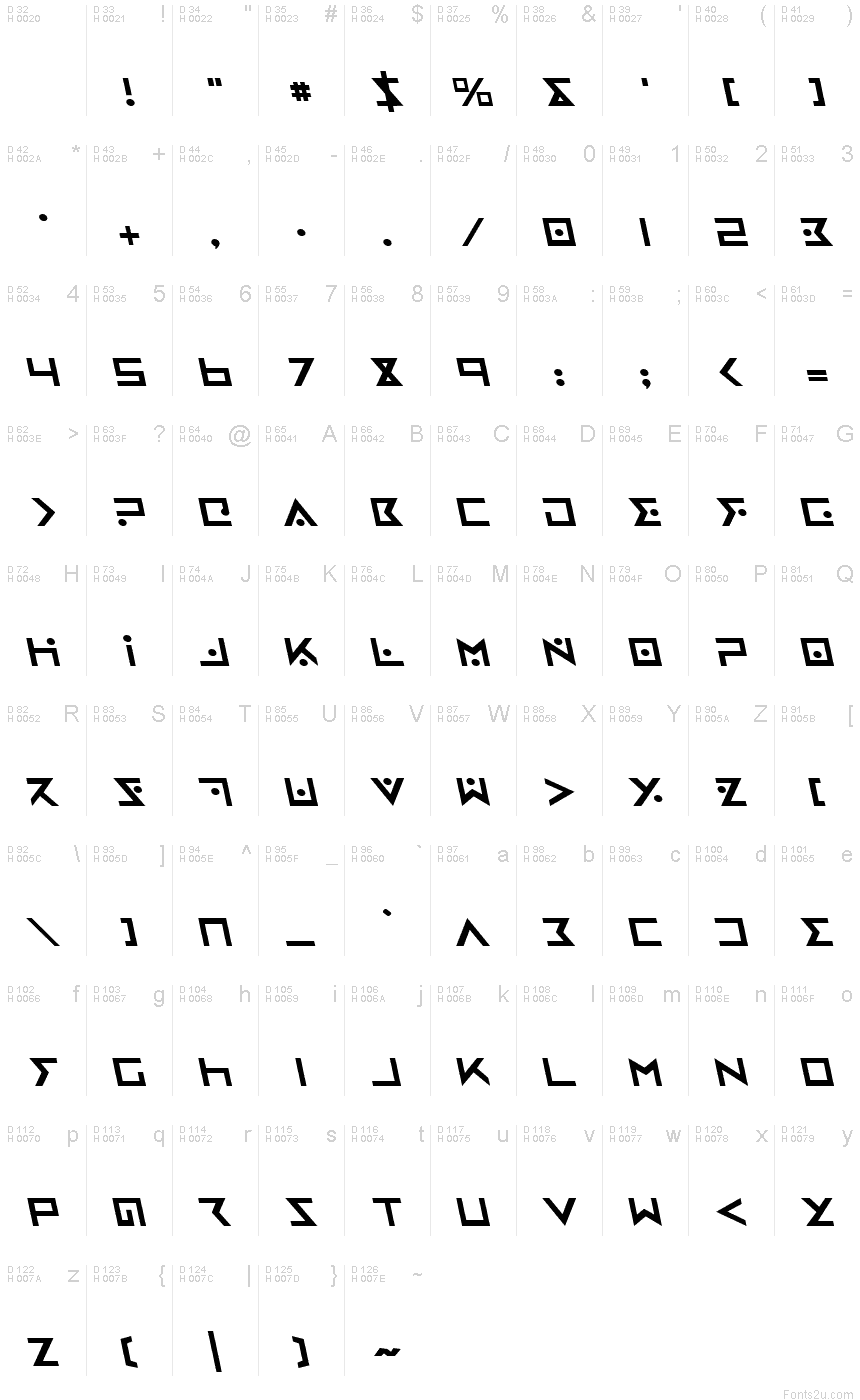
Iron Cobra Leftalic od Iconian Fonts to darmowy techniczny krój pisma typu display z wyraźnym sznytem science-fiction i ostrym, „pancerzowym” charakterem. Litery zbudowane są z ciężkich, kanciastych kresek z przyciętymi rogami, diagonalnymi cięciami i szerokimi, geometrycznymi prześwitami, co nadaje całości szybkiego, bojowego i lekko agresywnego wyglądu.
Naturalnie odnajduje się w logotypach gier, grafikach esports, nagłówkach plakatów, okładkach albumów i planszach tytułowych, gdzie zależy Ci na futurystycznym charakterze bez nadmiernego efektu neonu. Jako darmowy font świetnie sprawdza się również w krótkich elementach brandingowych, monogramach i etykietach typu interface, ponieważ ukośna geometria nadaje nawet krótkim słowom silne wrażenie dynamiki.
Iron Cobra Leftalic